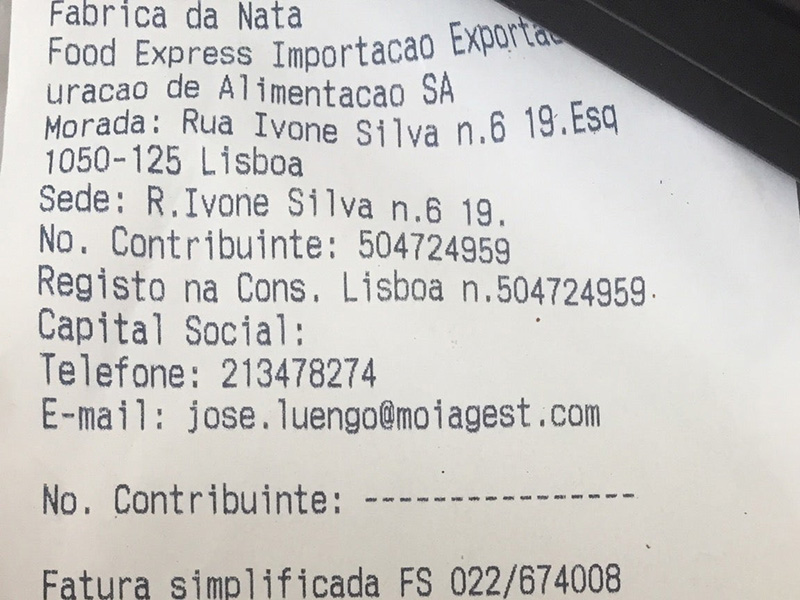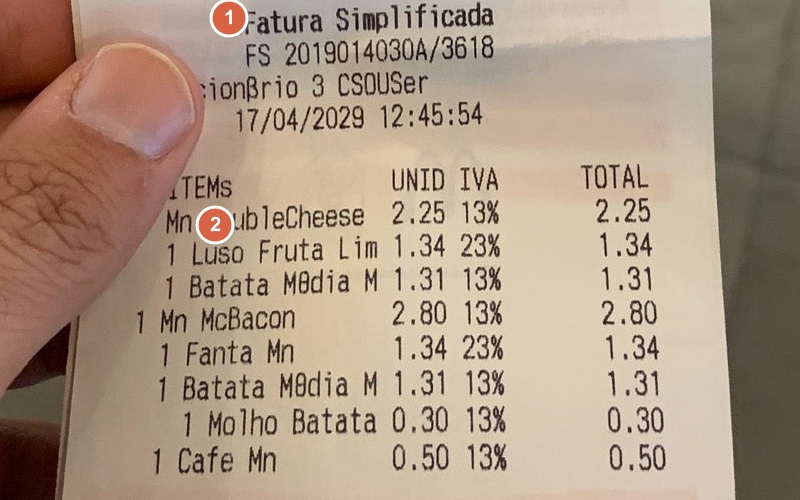
A fonte de fatura simplificada mais utilizada em Portugal (fontZ1)
Amostra impressa da fonte para fatura simplificada de um café em Portugal (❶fonteZ1 ❷fonteZ1-estreito)⤴
Amostra impressa da fonte para fatura simplificada de um pastelaria em Portugal (❶fonteZ1 ❷fonteZ1-largo)⤴
Amostra impressa da fonte para fatura simplificada de um pizzaria em Portugal (❶fonteZ1 ❷fonteZ1-largo)⤴
Amostra impressa da fonte para fatura simplificada de um restaurante em Portugal (❶fonteZ1 ❷fonteZ1-largo)⤴
Amostra impressa da fonte para fatura simplificada de um restaurante em Portugal (❶fonteZ1-largo ❷fonteZ1)⤴
Amostra impressa da fonte para fatura simplificada de um pastelaria em Portugal⤴
Amostra impressa da fonte para fatura simplificada de McDonald’s em Portugal (❶fonteZ1-negrito ❷fonteZ1)⤴
Amostra impressa da fonte para fatura simplificada de um restaurante em Portugal (❶fonteZ1-estreito ❷fonteZ1)⤴
Amostra impressa da fonte para fatura simplificada de um restaurante em Portugal (❶fonteZ1 ❷fonteZ1-estreito)⤴